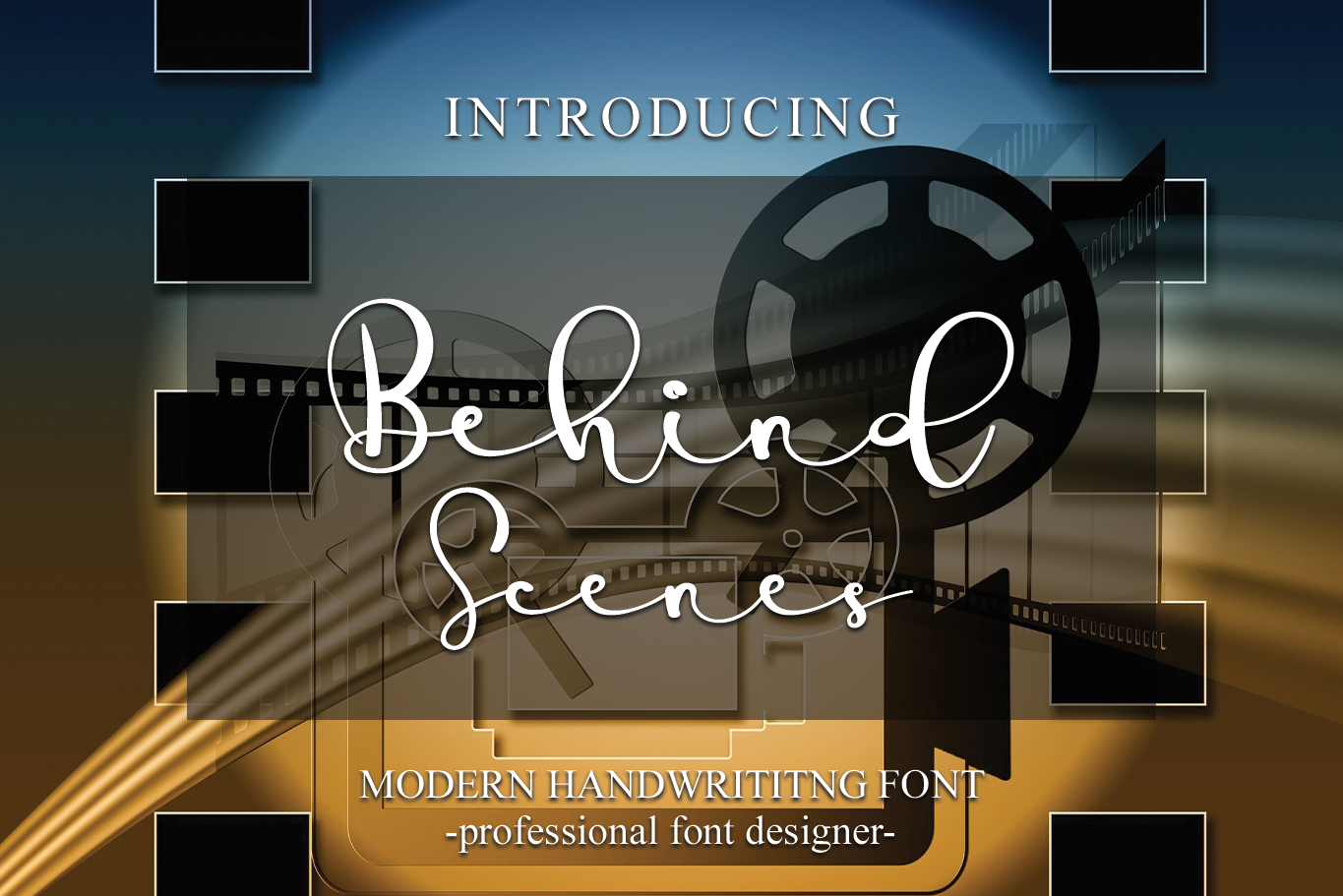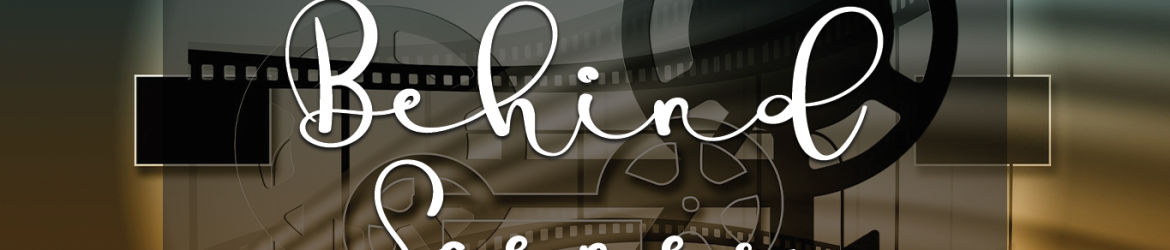
Behind Scenes Font – Download Grátis
Esta é uma fonte de escrita elegante, perfeitamente elaborada e detalhada. É a escolha ideal para adicionar originalidade a qualquer projeto ou criação, seja ela um logotipo sofisticado, uma citação poética ou até mesmo uma mensagem personalizada em papel. Ideal tanto para aqueles que buscam algo moderno e sofisticado quanto para aqueles que desejam trazer mais expressividade ao seu design, esta fonte será certamente um tesouro valioso para sua biblioteca de fontes. É perfeita para manusear em projetos de escrita gráfica, desde linhas lisas até texturas onduladas, tudo o que é necessário para dar vida a seus projetos. E se você está procurando por uma fonte que realmente ressalta seu trabalho, então esta font pode ser sua melhor escolha.